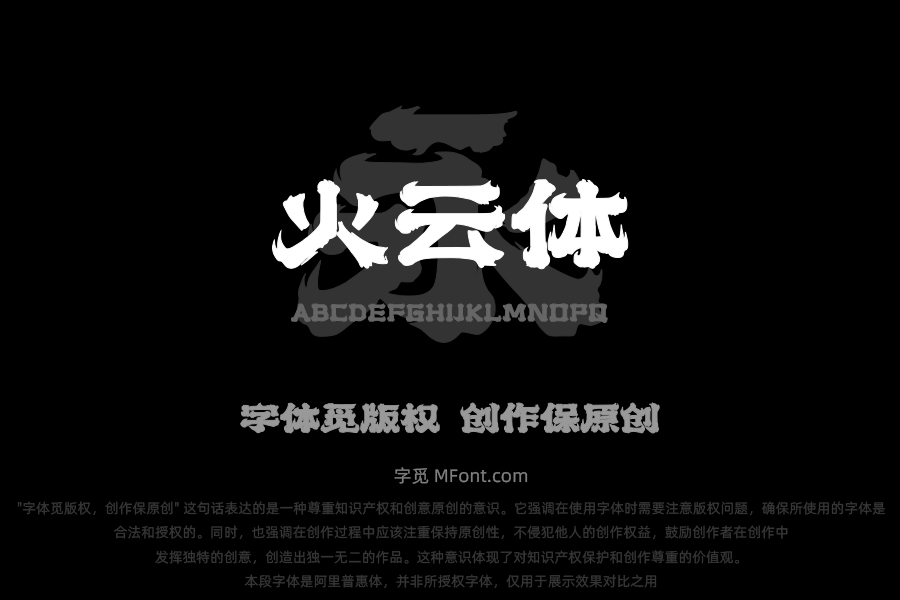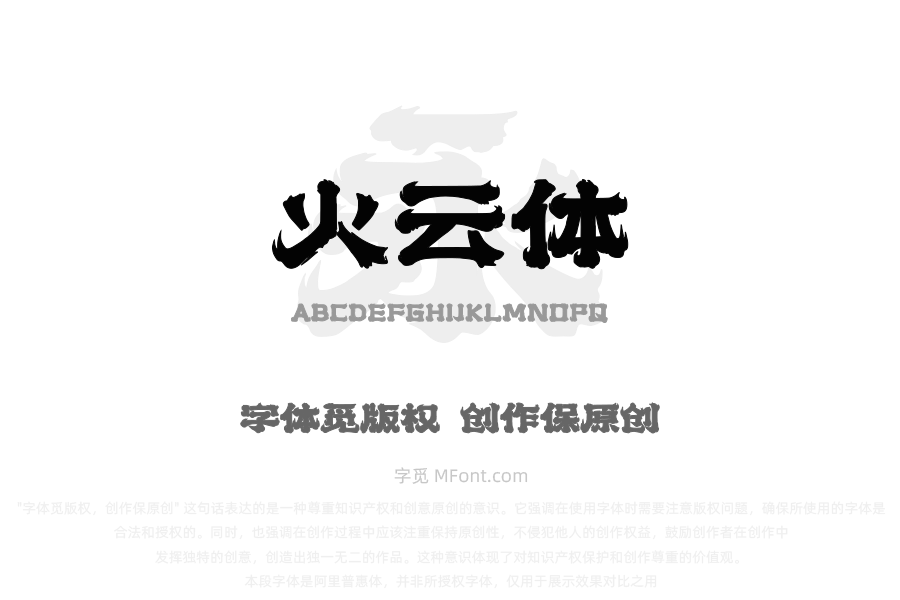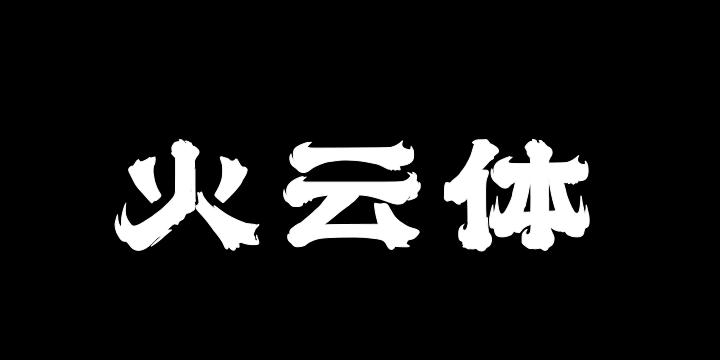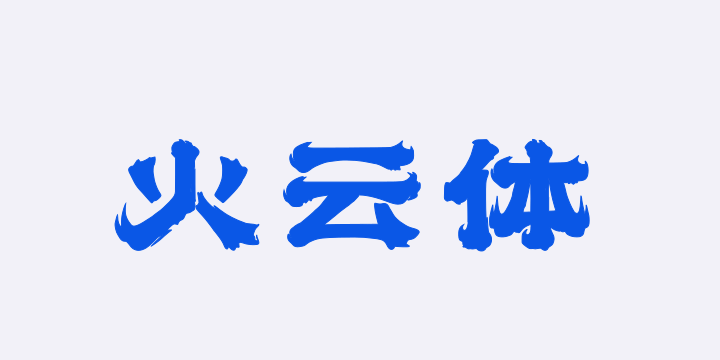
字体全名: 上首火云体
字体简介: 上首火云体,简体中文约6763字,横笔起笔如蚕头般圆润饱满,收笔似燕尾般舒展飘逸,竖笔挺拔如柱,转折处藏锋蓄力,笔画间的提按顿挫自然流畅。通过一些笔画断开的处理,确保结构均衡稳定的同时,既展现出传统书法的韵味,又不失现代设计的时尚感。
所属分类: 毛笔字手写体书法